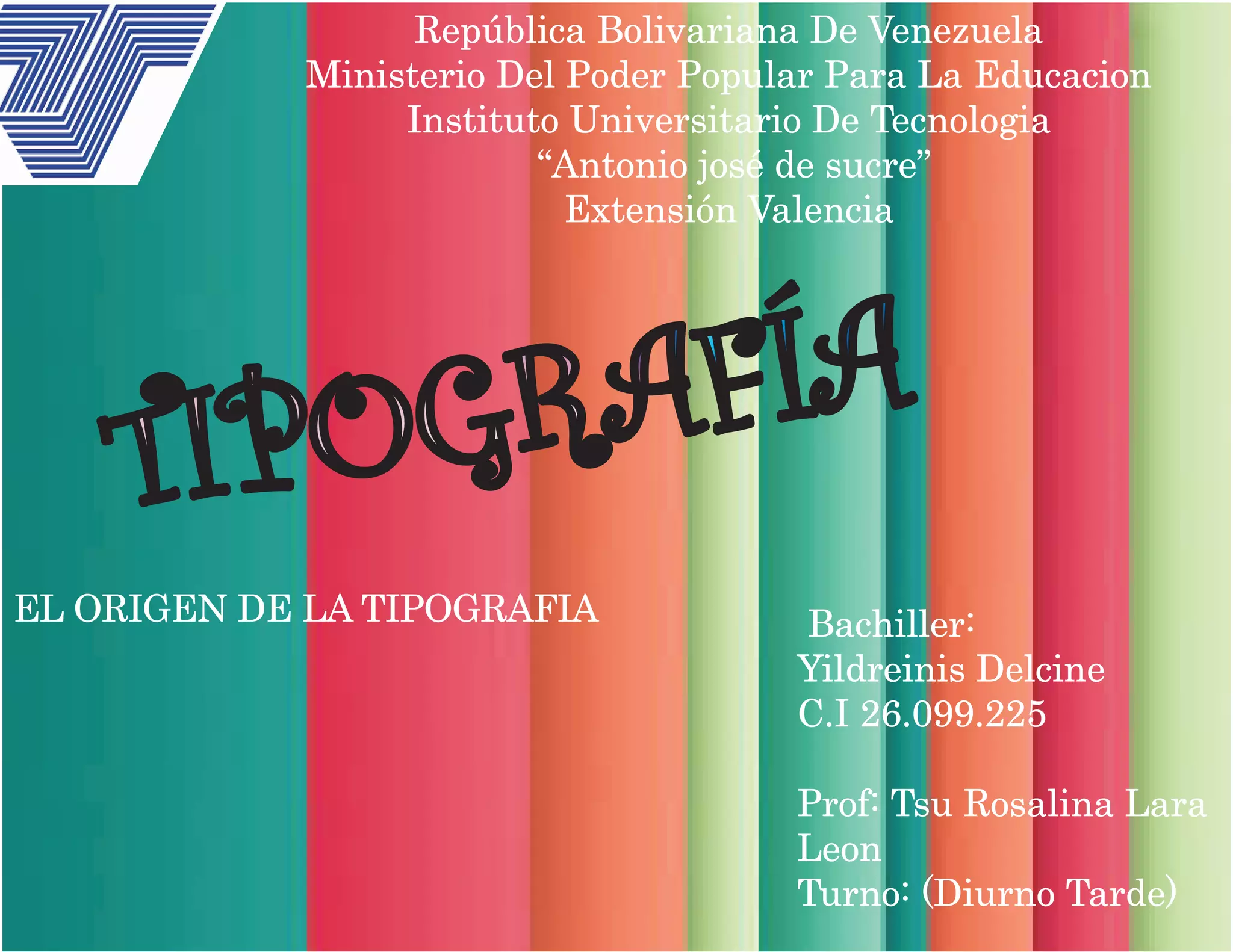
Definicion de tipografia
Es el arte, tecnica del manejo
y seleccion de tipos.
Es un oficio que trata sobre el
tema de las letras, numeros,
su tamaño y relaciones
visuales entre otras.
Es una disciplina que estudia
los distintos modos para
mejorar la emision grafica de
mensajes verbales.
Origen de la tipografia
Las primeras tipografias datan
desde antes de 2500 A.C, y fueron
manuscritos realizados sobre
madera, pergaminos de piel, hasta
que llego el papel.
Sus primeros usos fueron
acompañando monumentos,
grabados, dibujos, o pinturas.
Luego que el hombre aprendiera
sobre la escritura comenzo el arte
de embellecerla, y fue para entonces
cuando se comenzo la realizacion de
las diferentes tipografias hasta ahoa
se conocen.
Historia de la tipografia
La historia de la tipografía en una gran parte de la humanidad y
si se quiere se puede considerar uno de los orígenes del diseño
gráfico.
La primera escritura de la que se tienen registros que surgio en
mesopotania en el año 4000 A.C, y fueron los sumerios quienes
la idearon para identificar los productos en el comercio existente
entre los ríos. Se le atribuye a los sacerdotes y escribas que eran
los que encontraban con el poder y el conocimiento
Origen y anatomia del
tipo
Hablar de anatomia del tipo es hablar de la
forma de la letra de sus detalles mas
intimos, de la manera en que cada uno de
sus partes ha sido moldeada y
reinterpretada un gran impacto sobre la
funcion que esta cumple es importante
conocer como la presencia y la ausencia de
ciertos elementos puede afectar a una
determinada familia.
Su origen ha sufrido una constante
transformacion de lo antiguo a lo moderno
del lo sobrio a lo exagerado.
Durante siglos de evolución tipográfica se han ensayado diversos
términos, clasificaciones y sistemas. A medida que las nuevas ideas y
tecnologías han ido cambiando la naturaleza del tipo han ido
apareciendo nuevas formas de práctica tipográfica que han puesto en
crisis los sistemas de clasificación existentes. Entre ellos podemos
encontrar según Francis Thibodea
Tipo es: Igual al modelo o diseño de una letra determinada
LAS PARTES QUE COMPONEN UN TIPO:
Alturas de las mayúsculas: Es las altura de las letras caja alta.
Altura X; Altura de las letras de caja baja de las letras minúsculas
excluyendo los ascendentes y los descendentes.
El tipo y su clasificación
Anillo: Es el asta curva cerrada que forman las letrasb, p, o.
Ascendente: Asta que contiene la letra de caja baja y que sobresale
por encima de la altura x, tales como las letras"b, d y k".
Asta: Rasgo principal de la letra que la define como suforma o parte
mas esencial.
Astas Montantes; Son las astas principales o oblicuas deuna letra,
tales como la; L, B, V o A.
Asta Ondulada o Espina: Es el rasgo principal de la letra“S” en
mayúscula o en minúscula.
Asta Transversal: Rasgo horizontal de las letras; A, H, Fo T.Brazo:
Parte terminal que se proyecta horizontalmente o hacia arriba y que
no se encuentra incluida dentro del carácter, tal como se pronuncia en
las letras; E, K y L.
Serif Las fuentes Serif o de adorno tienen su origen en el pasado,
cuando las letras se cincelaban en bloques de piedra, pero resultaba
difícil asegurar que los bordes de las letras fueran rectos, por lo que el
tallador desarrolló una técnica que consistía en destacar las líneas
cruzadas para el acabado de casi todas las letras, por lo que las letras
presentaban en susextremos unos remates muy característicos,
conocidos con el nombre de Serif.
Del francés Sans “sin” Serif, serifa o patines. Las fuentes Sans Serif
están simplemente sin patines o pies, es decir, no tienen remates en
sus extremos.
Las fuentes Sans Serif, etruscas o de palo seco, hacen su aparición
en Inglaterra durante el siglo XIX. Entre sus trazos gruesos y
delgados no existe contraste, sus vértices son rectos y sus trazos
uniformes, ajustados en sus empalmes. Representan la forma natural
de una letra que ha sido realizada por alguien que escribe con otra
herramienta que no sea un lápiz o un pincel.
Manuscritas o ScriptLas
fuentes manuscritas o script
parecen cursivas o decaligrafía.
En el diseño de una
presentación digital,
estasfuentes se reservan para
acentuar el título principal, o
lafirma del autor, pues los
trazos más finos
puedendesaparecer,
comprometiendo la legibilidad.
La tipografia delsiglo XX La tipografía del siglo XX examina los principales aspectos que han dado forma a la historia del diseño tipográfico y también del diseño gráfico. Además de contar con más de 300 ilustraciones, el libro reflexiona sobre la cultura de la experimentación en el diseño tipográfico contemporáneo y presenta de forma clara su contexto histórico. La presente obra proporciona a los diseñadores, estudiantes y público en general una guía completa y de fácil comprensión sobre la tipografía del siglo XX y las cuestiones fundamentales que condicionarán la práctica tipográfica en el futuro.